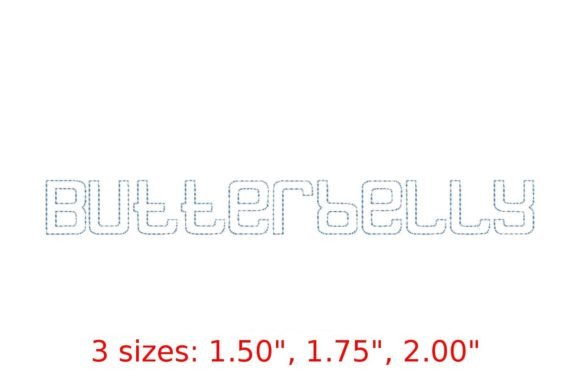
Butterbelly Bean Stitch Outline Font
De Butterbelly Bean Stitch Outline Font is een prachtig voorbeeld van minimalisme in de typografische wereld. Deze font, ontworpen met een focus op eenvoud en functionaliteit, biedt een unieke combinatie van stijl en gebruiksvriendelijkheid. Het is perfect voor ontwerpers die op zoek zijn naar een lettertype dat zowel modern als tijdloos is, waardoor het zichzelf steeds weer bewijst in diverse projecten.
Bouwkwaliteit en technische details
Het Butterbelly Bean Stitch Outline Font is gebouwd met precisie en aandacht voor detail. Het lettertype bestaat uit scherpe contouren en een gladde, vloeiende lijnstructuur, wat resulteert in een heldere leesbaarheid, zelfs bij kleinere lettergrootte. De font bevat een volledig set van karakters, inclusief hoofd- en kleine letters, cijfers, en speciale tekens, waardoor het zeer flexibel is in toepassing. Het is compatibel met verschillende softwareplatforms, waaronder Adobe Creative Suite, waardoor het gemakkelijk te integreren is in uw huidige workflow.
Voor wie is dit product het beste?
Dit lettertype is ideaal voor grafisch ontwerpers, webontwikkelaars, en iedereen die waarde hecht aan eenvoud en elegantie in hun visuele communicatie. Of u nu bezig bent met het ontwerpen van een nieuw logo, het creëren van een website, of het produceren van printmateriaal, de Butterbelly Bean Stitch Outline Font past naadloos in elk project. Het is vooral geschikt voor creatievelingen die op zoek zijn naar een minimalistisch, maar krachtig lettertype om hun boodschap over te brengen.
Tip: Combineer dit lettertype met een eenvoudige, bold serif-font voor titels, om een mooi contrast te creëren dat de aandacht trekt zonder afbreuk te doen aan de eenvoud van uw ontwerp.
Hoe het zich verhoudt tot de concurrentie
Vergeleken met andere minimalistische fonts zoals Helvetica of Futura, onderscheidt de Butterbelly Bean Stitch Outline Font zich door zijn unieke stiksel-effect. Dit maakt het niet alleen functioneel, maar ook esthetisch aantrekkelijk, waardoor het perfect is voor projecten waarin textuur en karakter gewaardeerd worden. Terwijl andere fonts misschien meer traditioneel blijven, biedt Butterbelly een frisse, moderne draai aan de klassieke minimalistische stijl.